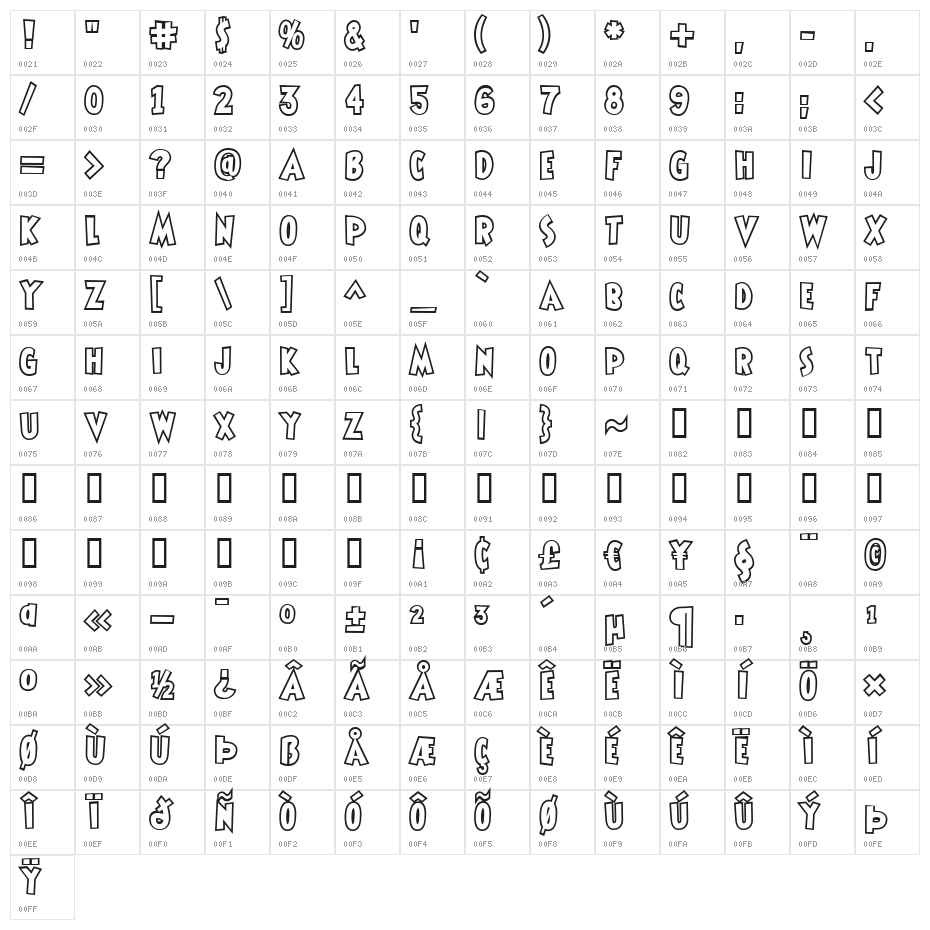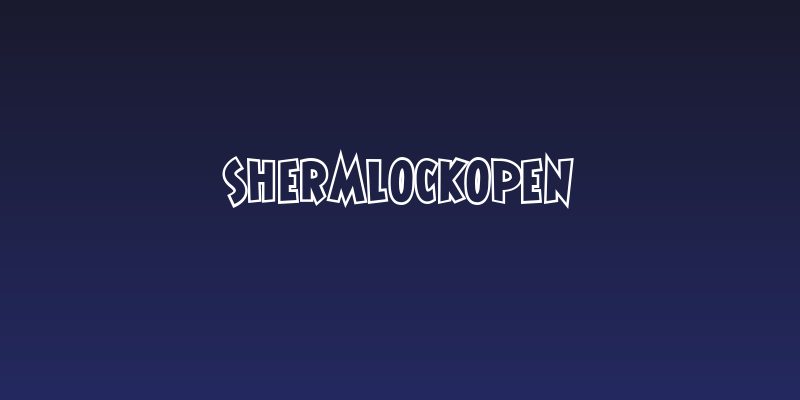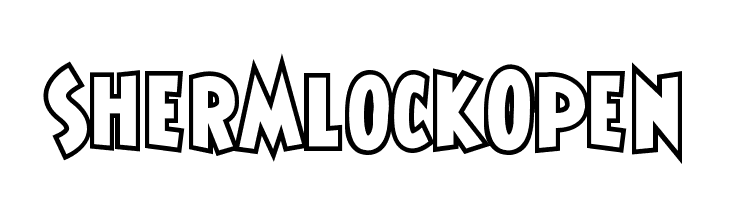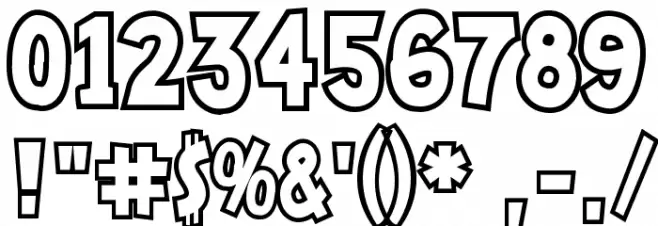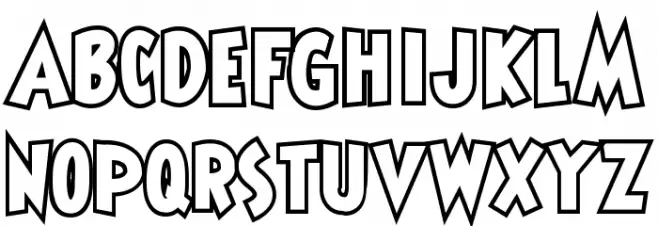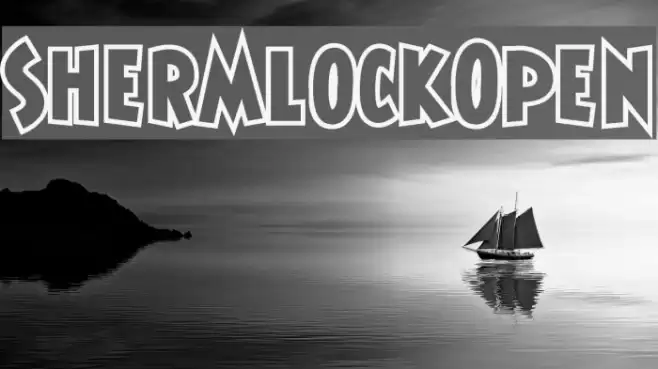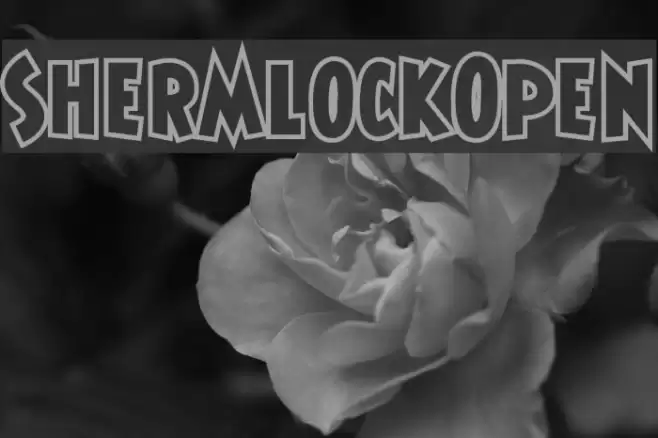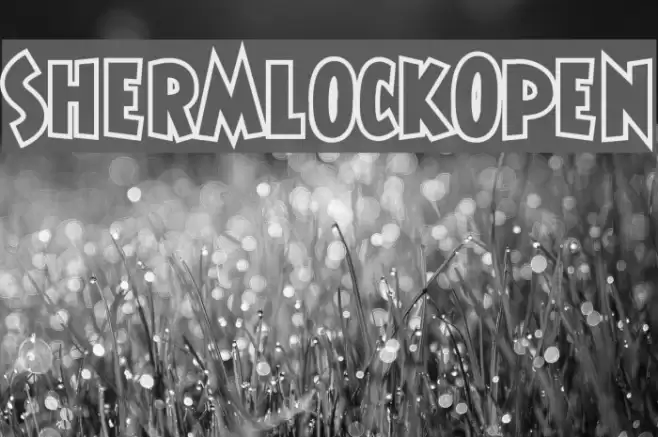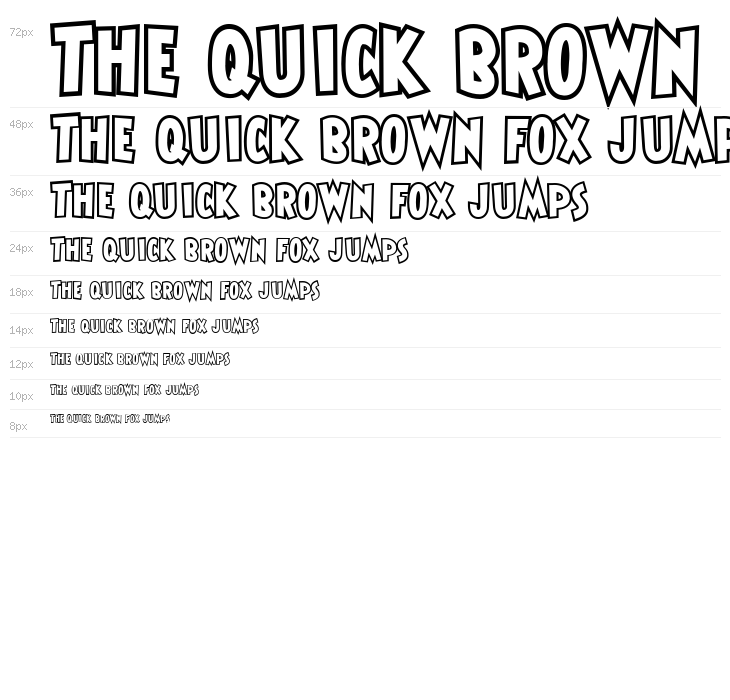
ShermlockOpen Font
Fonts by Daniel Gauthier
| 全体的なスタイル | Playful, Cartoonish |
| 用途 | Headlines, Posters, Branding |
| おすすめプロジェクト | Perfect for children's books, comic strips, playful branding, and eye-catching posters. |